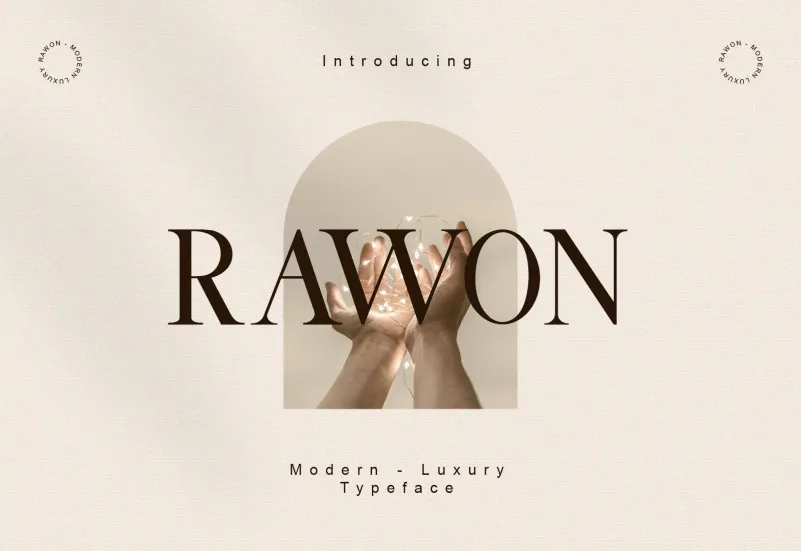
Aqui está uma descrição em português para a página de download da font ‘Rawon Font’, mantendo os requisitos fornecidos: A Rawon Font é perfeita para qualquer projeto, seja ele um logo ou até mesmo cartazes e materiais promocionais. Esta fonte moderna e contrastada oferece uma leitura fácil que se adapta a várias aplicações, como logotipos, convites de casamento, t-shirts, etiquetas de embalagens e até mesmo material de propaganda. Suas linhas ergonômicas garantem um visual atraente em diversos ambientes, tornando-a uma escolha ideal para designers, gráficos ou qualquer pessoa que esteja procurando por uma fonte de confiança para seus trabalhos. Com sua estética clean e contrastada, você pode explorar inúmeras possibilidades criativas com Rawon Font. Suas linhas finas e bold permitem experimentar diferentes tonalidades e tamanhos para criar um design único, adaptável a diversos usos comerciais ou pessoais. Não importa o tipo de material em que você esteja trabalhando: seja logotipo, cartaz ou qualquer outra forma de comunicação visual, Rawon pode ajudá-lo a destacar sua marca com estilo e eficácia.